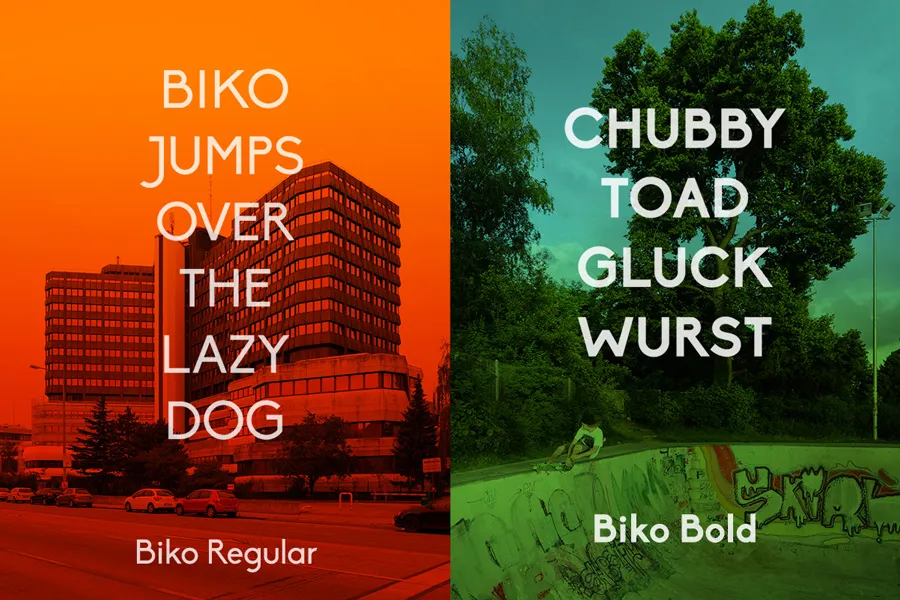
Biko é uma fonte sans-serif geométrica com um tom carismático mas robusto. Perfeita tanto para exibição quanto para texto e logotipos, esta família de fontes homenageia Steve Biko, o ativista anti-apartheid sul-africano. A Biko Font Family se apresenta em quatro versões: Ligeira, Regular, Negritas e Escuro. Essa escolha é uma forma de tributo a um líder que lutou por liberdade e igualdade, inspirando aqueles que desejam moldar mudanças sociais e políticas. Esta família de fontes oferece um equilíbrio perfeito entre simplicidade e força, tornando-a ideal para ambientes que valorizem tanto a estética quanto o impacto comunicativo.